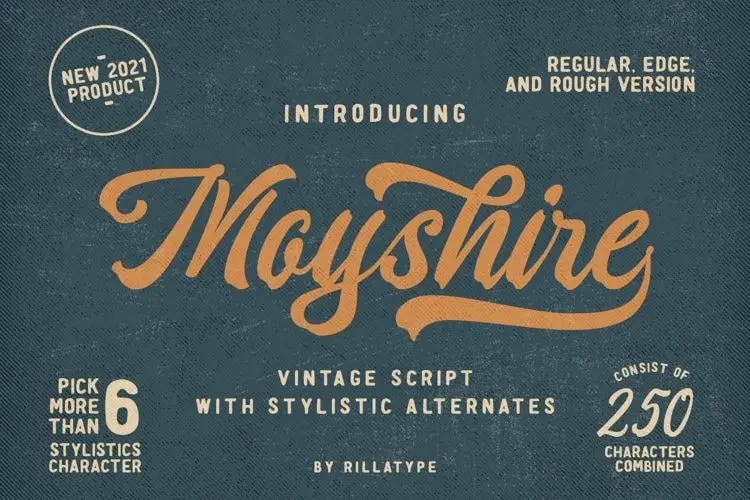
Moyshire Script Font – Download Grátis
Moyshire Script Font é uma fonte tipográfica script que transborda elegância com sua forma fluida e arredondada. Crie por Rillatype, incorporando um toque de pincel para dar ao tipo uma aparência mais marcante e atraente aos olhos. Esta fonte é perfeita tanto para criações de marca, ilustração ou mesmo design de roupas. A Moyshire Script Font também oferece suporte a múltiplas línguas, números e símbolos. O catálogo do nosso produto inclui três versões distintas: Regular, Rough e Edge. Esta fonte, além de ser elegante e sofisticada, tem um toque que torna-a adequada para diversos tipos de projetos. Seja uma criação de identidade visual, artes gráficas ou até mesmo o design de roupas, a Moyshire Script Font trará um toque diferenciado e único ao seu trabalho. Ela é perfeitamente adaptável à sua necessidade específica de cada projeto, oferecendo diferentes opções de estilo que vão do elegante ao marcante. Sua versatilidade faz da Moyshire Script Font uma fonte indispensável para qualquer designer gráfico ou criador de conteúdo. Aproveite a chance de adquirir esta fonte incrivelmente rica em detalhes e personalização, que não só oferece estilos diferentes mas também suporta múltiplas línguas e símbolos, tornando-a uma opção versátil para qualquer projeto gráfico.